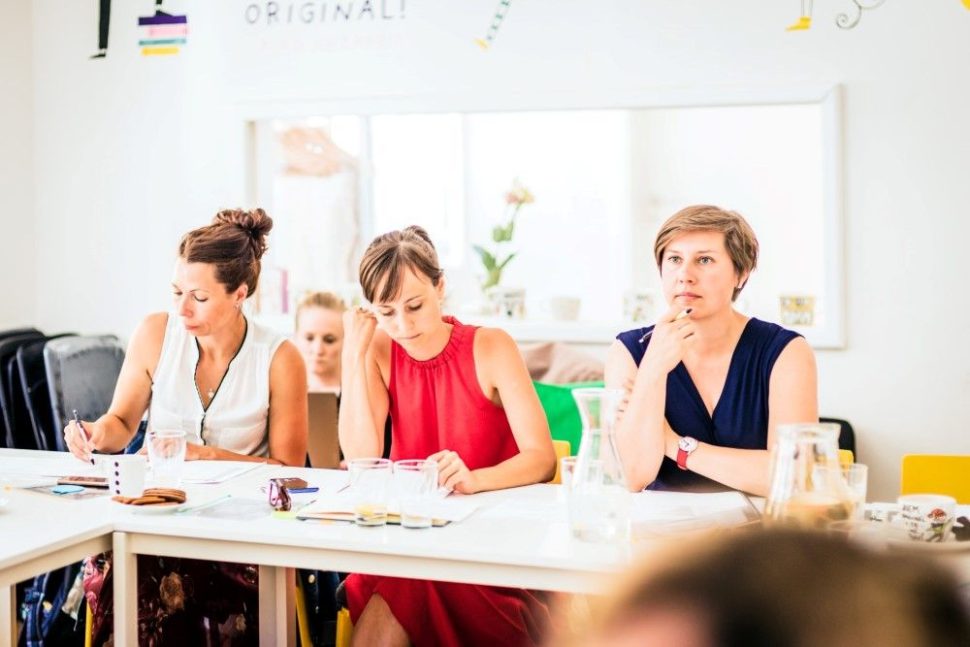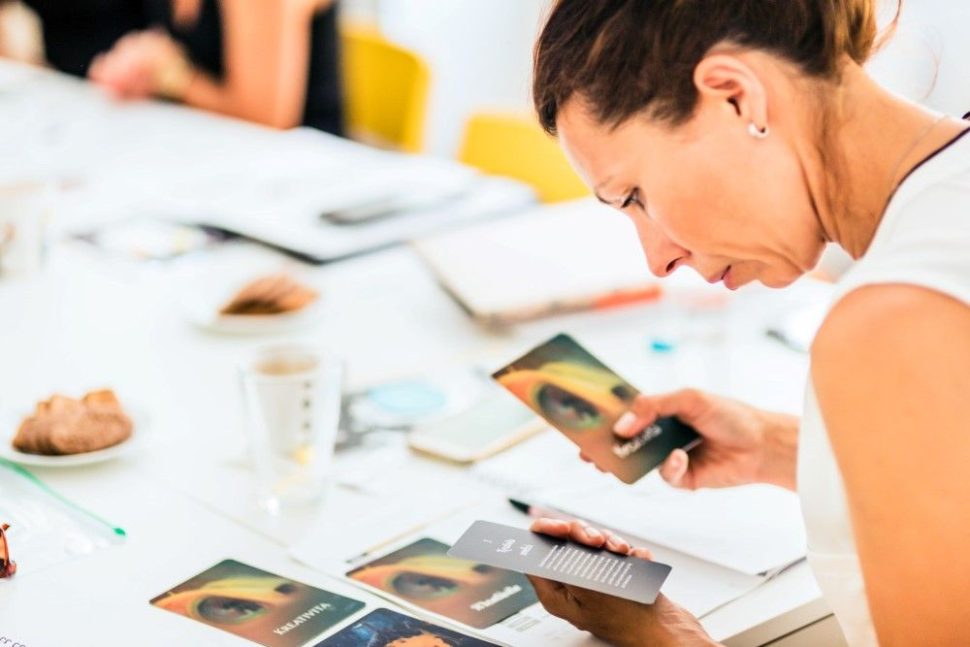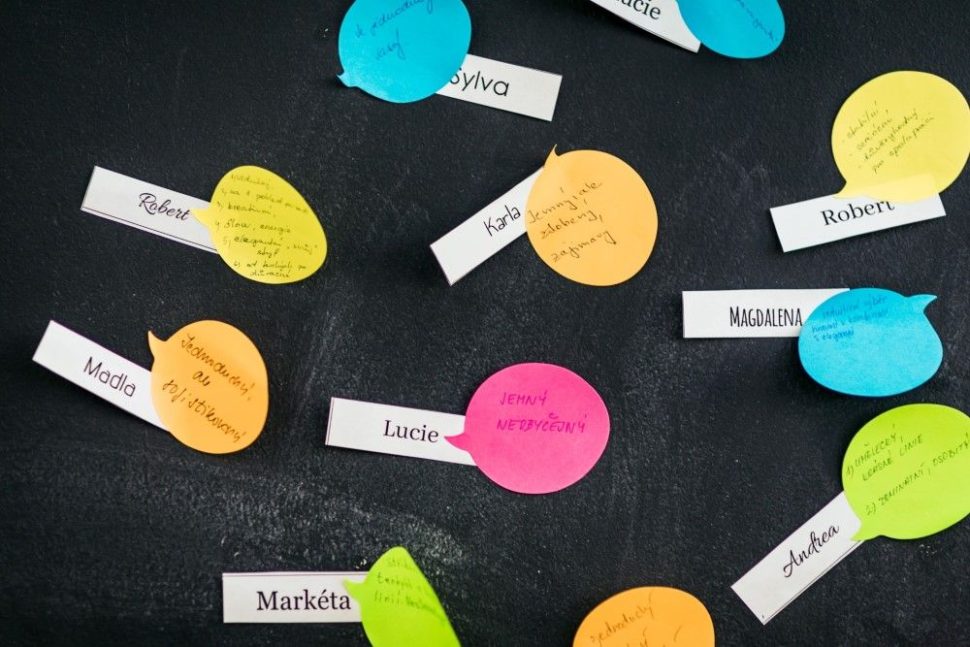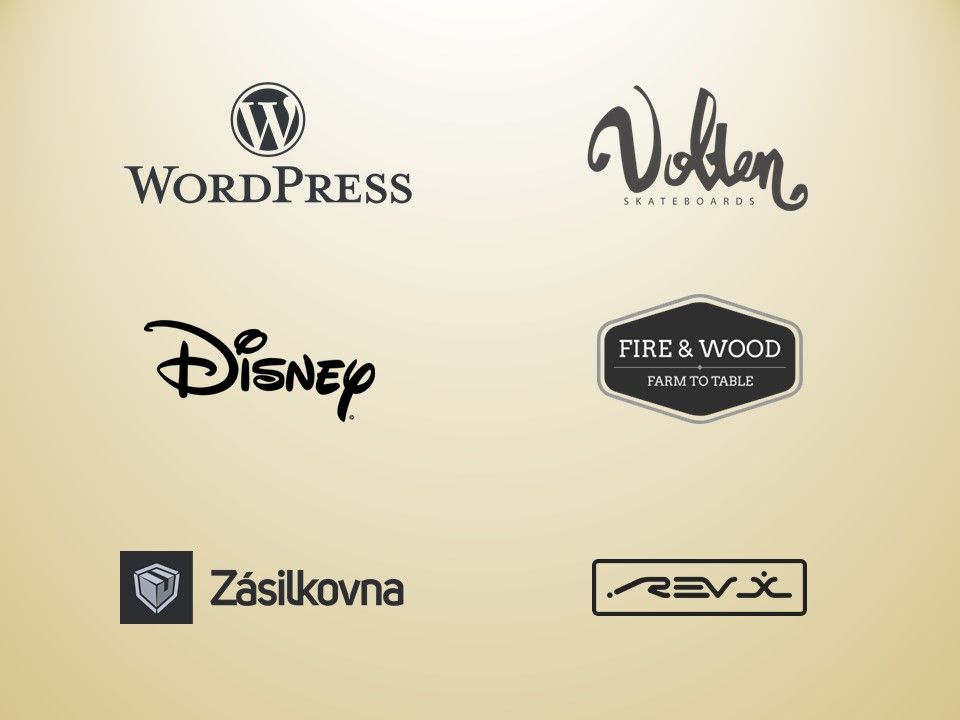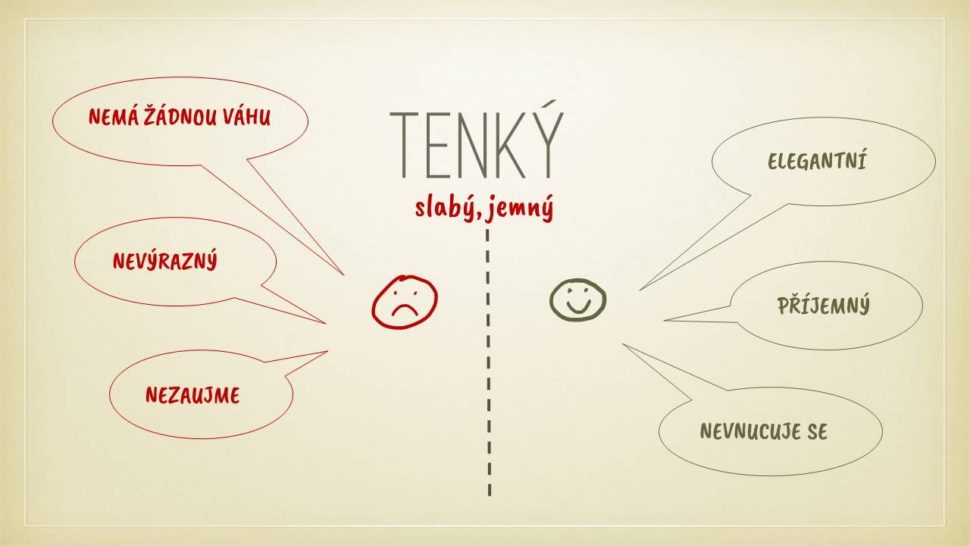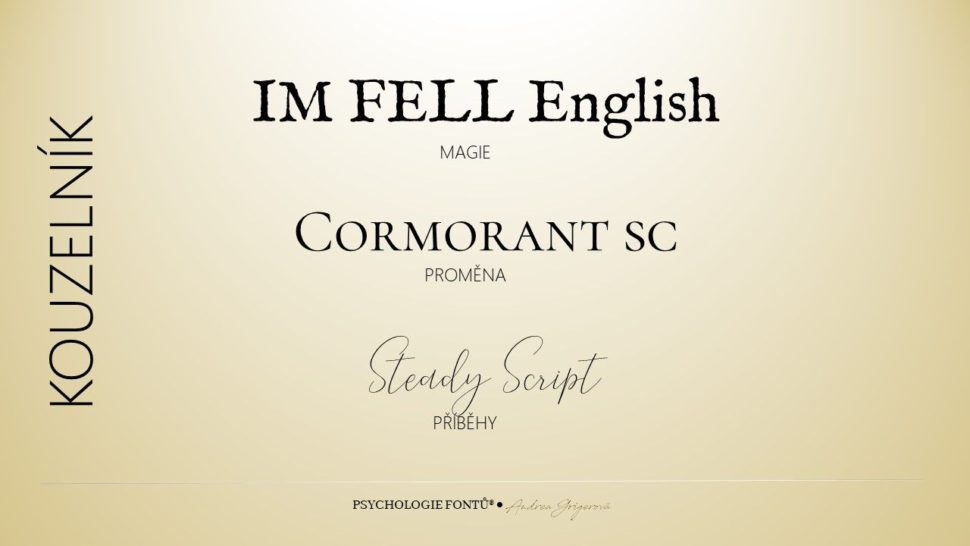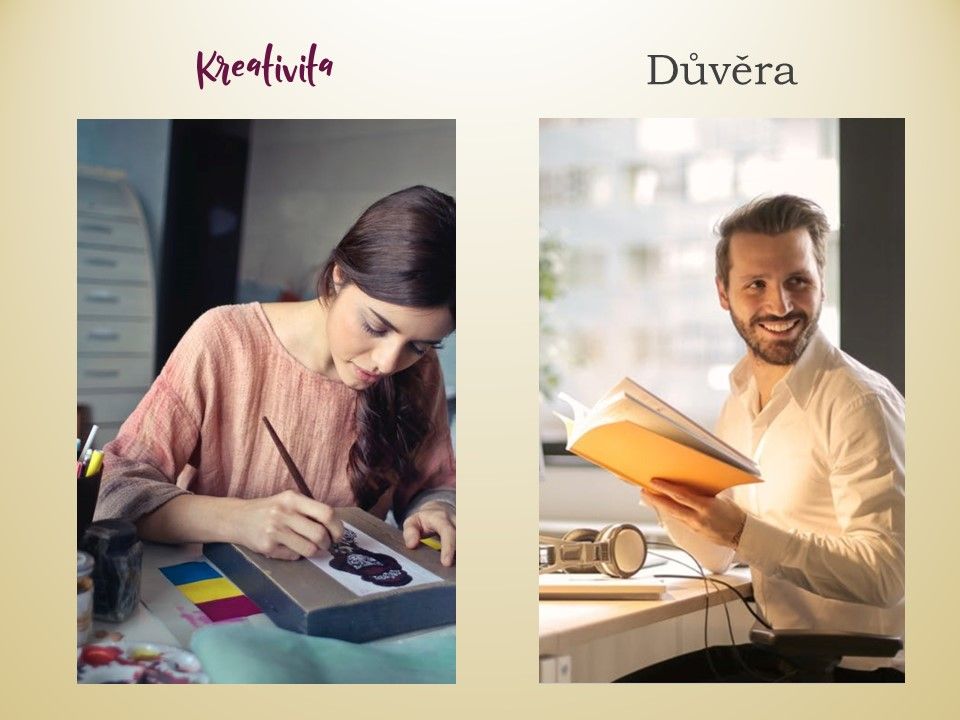
Praktický online workshop
FONTY V MARKETINGU
Objevte, jak silným nástrojem jsou fonty pro marketingovou komunikaci a pronikněte do jejich fascinujícího světa. Naučte se, jak s pomocí fontů vyvolat tu správnou emoci.
PRO KOHO SE WORKSHOP HODÍ?
- Pro markeťáky a markeťačky,kteří komunikují s grafiky a chtějí mít jasno v tom, jak ve výběru fontů postupovat, aby měli argumenty pro grafiky i klienty.
- Pro grafiky a webdesignérykteří vybírají fonty intuitivně, ale chtěli by získat pevnou půdu pod nohama a argumenty pro svůj výběr.
- Pro brand manažery a manažerky,kteří mají na starosti fonty coby součást vizuální identity.
"Velmi doporučuji všem, kdo pracují se značkou, připravují strategie nebo posuzují tištěné či on-line marketingové materiály."
NÁPLŇ WORKSHOPU
6 HODIN TEORIE I PRAKTICKÝCH CVIČENÍ. Skvělý mix AHA momentů, teorie a zážitků. Budete v kůži grafika, markeťáka i klienta. Nejenom, že pochopíte, v čem je síla fontů, ale naučíte se tuto sílu používat. Naučíte se fonty vědomě vybírat. Budete umět obléci texty klientovi na míru a vzbudit emoce, které přitáhnou nebo odradí klienty.
HARMONOGRAM:
1. CO JE PSYCHOLOGIE FONTŮ?
Co to je a kde se vzala? Kde se s ní potkáváte, kde má význam a jakým způsobem nás ovlivňuje. A jak jí můžete využít?
2. JAK TO FUNGUJE?
Reagují na fonty všichni stejně? Jak můžu vědět, jaký font přitáhne zákazníky? Co se jim asi honí hlavou?
3. JAK VZBUDIT EMOCE?
Dokážu pracovat s barvami a archetypy, ale jak na to napasovat výběr fontu? Tak, aby vzbudil emoce, které chci?
4. JAK VYBÍRAT?
Existuje konkrétní návod, jak a podle čeho fonty vybírat?
Nějaká typologie, které bych se mohl chytit? Na workshopu získáte 8krokový návod, jak vybrat správný font pro konkrétní použití.
5. MARKETING
Další puzzle do skládačky vizuálního stylu. Osaháte si, jak změna fontu zcela zásadně změní vnímání značky.
Dostanete do ruky nástroj, jak fonty vybírat, porozumíte třídění fontů podle charakteru. A hlavně získáte jednoznačné argumenty, když bude váznout komunikace s klienty nebo grafiky.
"Ač jsou fonty už roky mým denním chlebem, nenechala jsem fontový workshop ujít. Byla to parádně interaktivní jízda a všechny nabyté informace jsme si hned vyzkoušeli na celé řadě zábavných her a cvičení. Za sebe můžu vřele doporučit!"
DÍKY WORKSHOPU ZÍSKÁTE:
- 1Konkrétní argumenty pro komunikaci s klientem/grafikem/markeťákem.Budete umět přesně vyjádřit, co od fontu potřebujete a odůvodnit jeho použití. Vyhnete se nekonečným tahanicím typu "ten, který navrhujete, se mi nelíbí, ale nevím, jaký se mi líbí".
- 2Další nástroj budování značkyPsychologii barev už používáte, teď budete vědomě využívat i psychologii fontů. Víte, že právě font vyhrál Obamovi volby?
- 3Cestu k emocím cílové skupinyNebudete fonty vybírat intuitivně, ale vědomě a cíleně podle toho, jaké mají u cílové skupiny vyvolat emoce.
- 4SebejistotuAž budete příště vybírat fonty, hodnotit grafické návrhy nebo připravovat tištěné i online materiály.
"Dostal jsem něco, co jsem absolutně nečekal. Koncentrovaná nálož informací během 5 hodin. Největší radost mám z toho, že volbu písma teď umím odůvodnit sám sobě, natož ostatním. A taky jsem získal skvělý návod, jak v 8 krocích "zvolit" písmo."
CO DALŠÍHO ZÍSKÁTE?
- JEDINEČNÉ KNOW-HOW Psychologie fontů®6 let testuji, konzultuji, bádám a hledám souvislosti. O to vše se s vámi ráda podělím. A těším se na vaše poznání a úžas, jak moc vám schopnost rozumět řeči fontů změní práci. Posune ji na úplně jiný level. Ale pozor, je to jako s Jiříkem a hadem. Jak jednou porozumíte řeči fontů, budou na vás mluvit stále a všude.
- MATERIÁLY KE ŠKOLENÍNebudete sedět s prázdnýma rukama, během školení si doslova a do písmene osaháte spoustu písmenek. Samozřejmostí je pdf s nejdůležitějšími informacemi, ať nemusíte vše zapisovat.
- KARTY FONTOHRÁTKYLuxusní karty, které Vám pomohou vnímat energie jednotlivých fontů. Můžete je využít jako ukázku při diskuzi s klientem, jako zábavnou hru nebo jako inspiraci > více o kartách
OHLASY ÚČASTNÍKŮ
Ač jsou fonty už roky mým denním chlebem, nenechala jsem si ujít fontový workshop Psychologie fontů v úterý v Brně. Byla to parádně interaktivní jízda, která svižně ubíhala při poutavém odhalování emocí fontů, které by měly při správně zvoleném typu písma v příjemcích reklamy nebo čtenářích textu vyvolávat. Zastavili jsme se u serifů, scriptů, sans serifů, tučných nebo tenkých písem, kurzívy či rovných liter nebo kontrastu tahů a všechny nabyté informace jsme si hned vyzkoušeli na celé řadě zábavných her a cvičení. Za sebe můžu vřele doporučit!
Školenie mi definitívne zmenilo pohľad, ako sa dívam na fonty okolo seba. Som schopný rozlíšovať podprahové informácie, ktoré font v sebe nesie. Školenie jednoznačne odporúčam každému, kto sa zaujíma o efektívne využívanie fontov.
Pro mě osobně byl velmi zajímavý, musím opravdu psychologii fontů přiznat opravdu velkou váhu. Po semináři ještě větší, než jsem před ním vůbec byla schopna. Seminář se mi líbil jasným záměrem, přehledným uspořádáním i atmosférou. Semináře si vybírám pečlivě. U Vašeho semináře nelituji, splnil víc, než jsem očekávala. Takže teď již jen hurá do praxe.